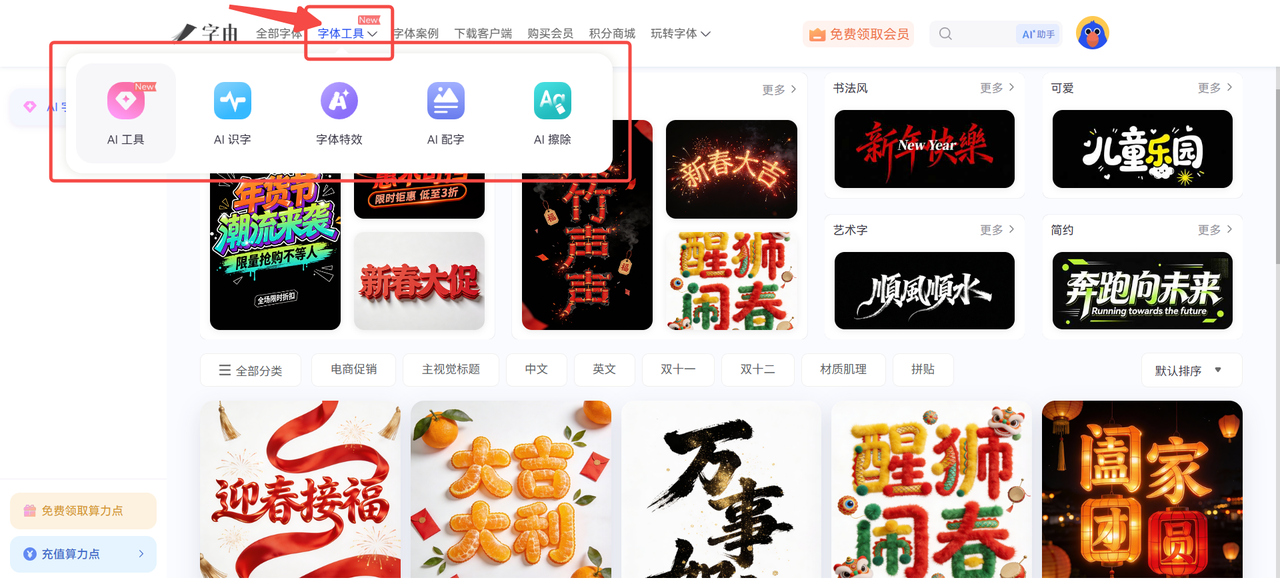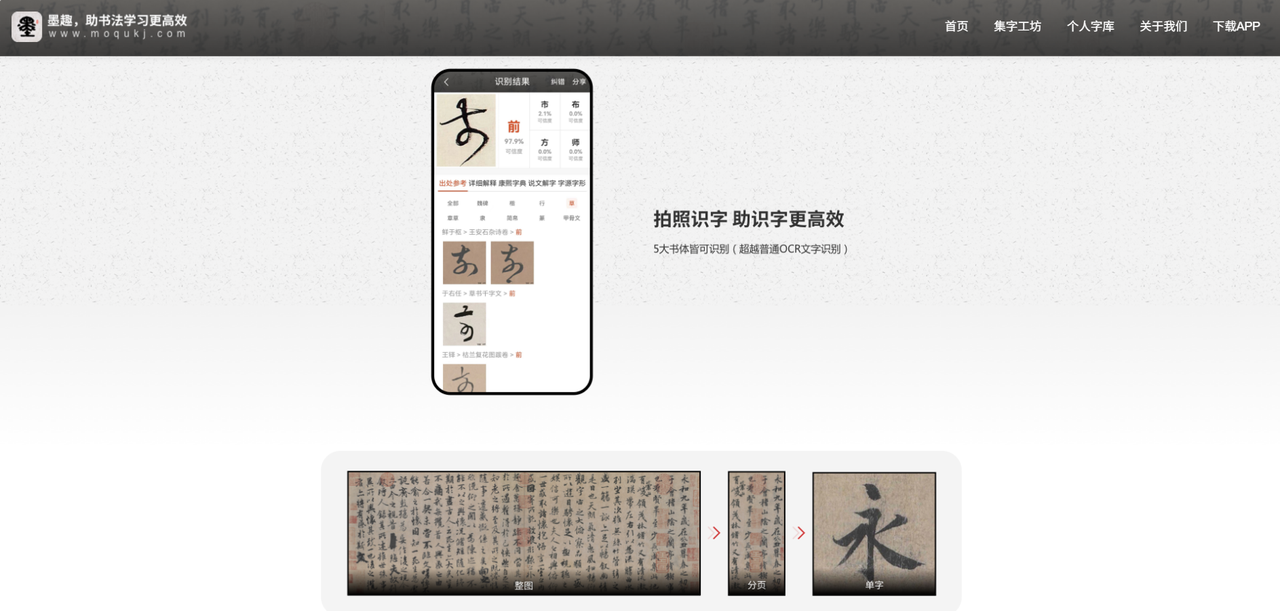
1.字由
字由是一个拥有海量免费可商用字体资源的字体工具,众多设计师亲测好用。字由提供 5000+ 精选字体,有各种风格的免费书法字体下载服务,例如钟齐志莽行书、汉仪程行简、苍耳周珂正大榜书、汉仪书魂体简以及汉仪孙万民草书等多种热门书法字体都可下载商用,无论是正式场合还是轻松愉快的应用场景都完美匹配,通过不同的书法字体下载应用展现出独特的设计风格,让你的设计别具一格,是一个设计师私藏的免费书法字体下载网站。
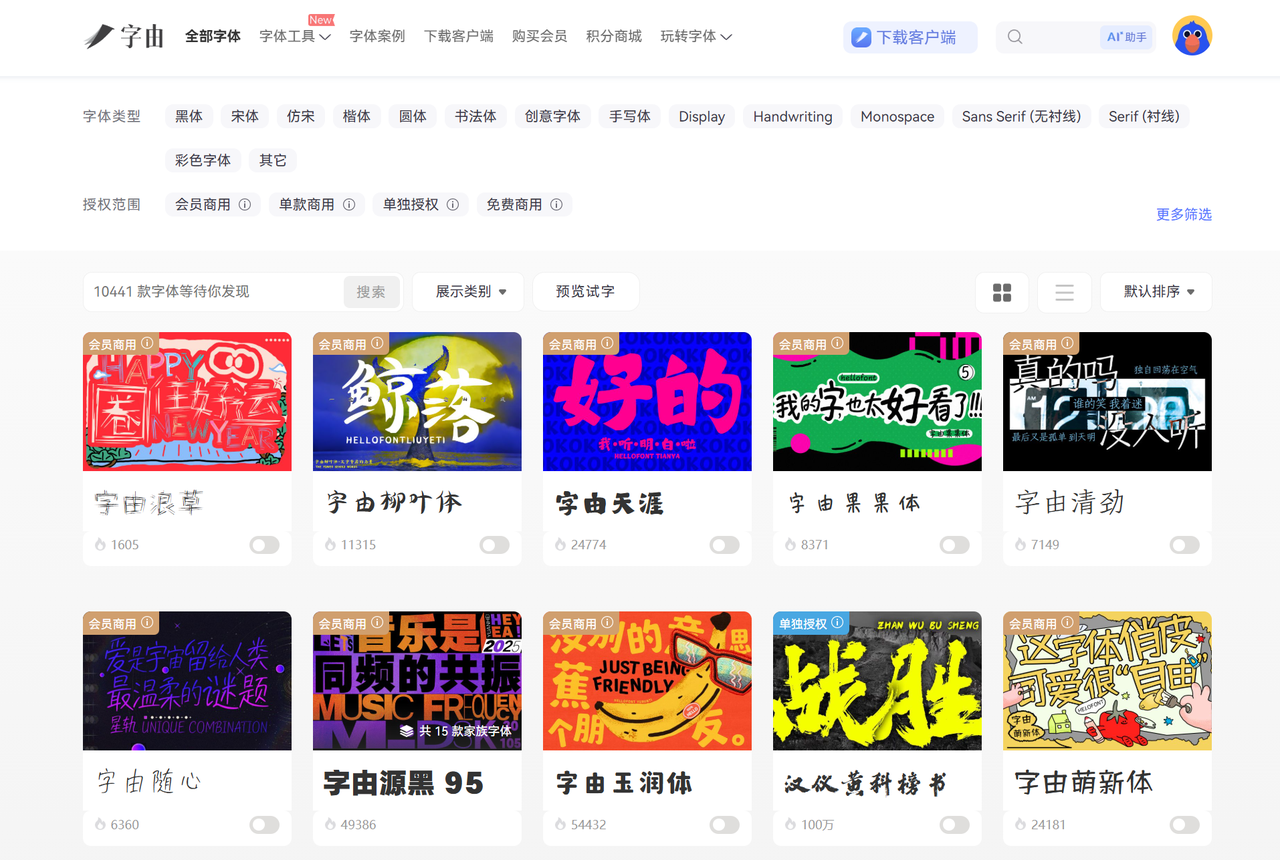
2. 墨趣书法
墨趣书法是我在查找碑帖资源时偶然发现的一个宝藏免费书法字体下载网站,内置 2000+ 经典碑帖资源,120万+ 张高清碑帖图片。这个网站收录了大量免费商用书法字体,方便用户下载学习使用,字体版权也做了清晰标注,明确了可使用范围。另外,该网站的书法字体资源涵盖古今,既有颜真卿、柳公权等名家书法的数字化字体,也有现代设计师原创的免费书法字体,风格多样,任君选择。如果你不仅需要免费书法字体下载,还想深入了解书法文化、提升字体运用技巧,这款软件我想会是很好的选择。
3.100font
100font 目前收录了 1500+ 字体资源,拥有丰富的免费书法字体下载资源,亲测好用。它按照语言、类型和授权进行分类,涉及了英文、日文、韩文等多种语言的免费书法字体下载服务,有手写书法字体,创意书法字体、衬线字体等多元风格,纯纯是优秀设计师私藏版的免费书法字体下载网站,上面的书法字体又全又好用,精准适配多元应用场景,不管你的设计作品是哪种设计风格都能 hold 住~如果你找不到合适的免费书法字体下载资源,可以多看看,也许会有你喜欢的书法字体资源。